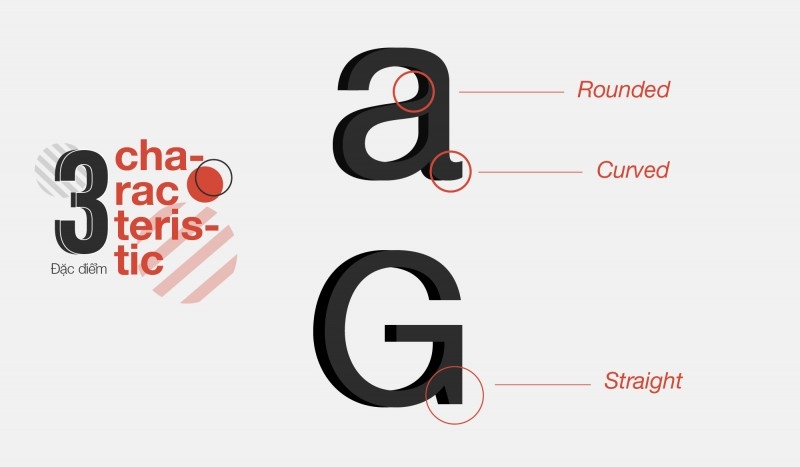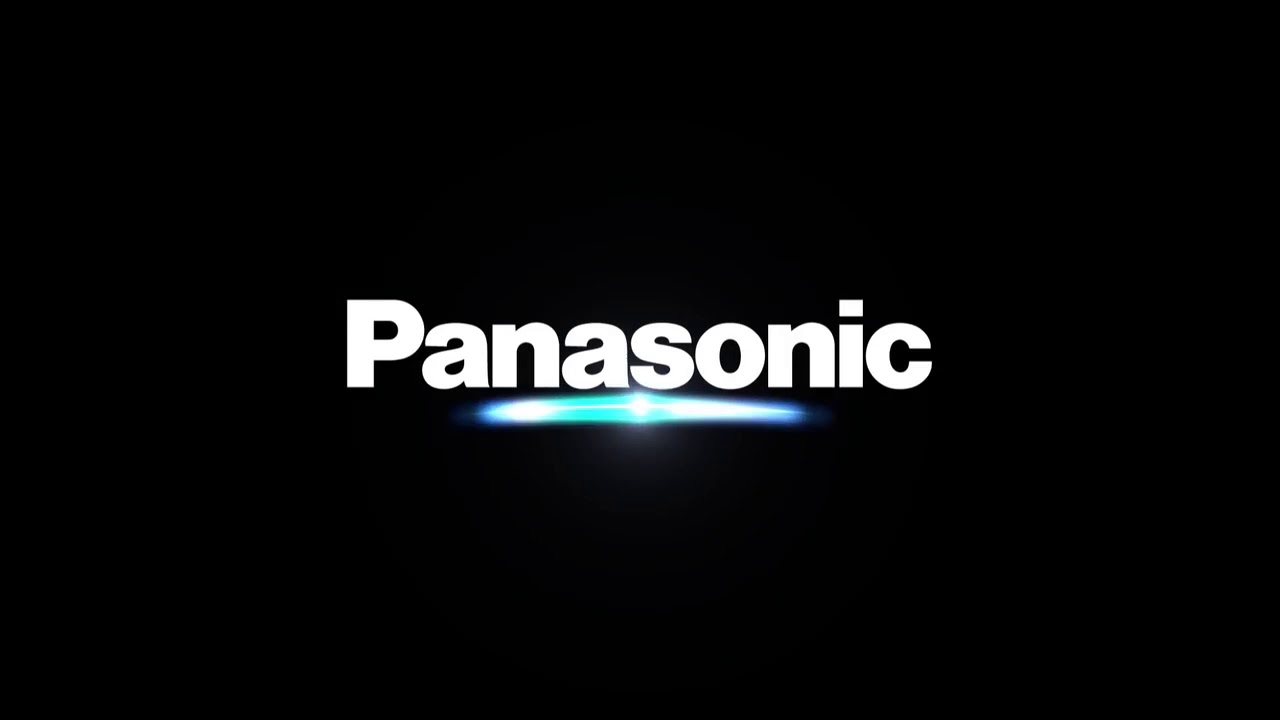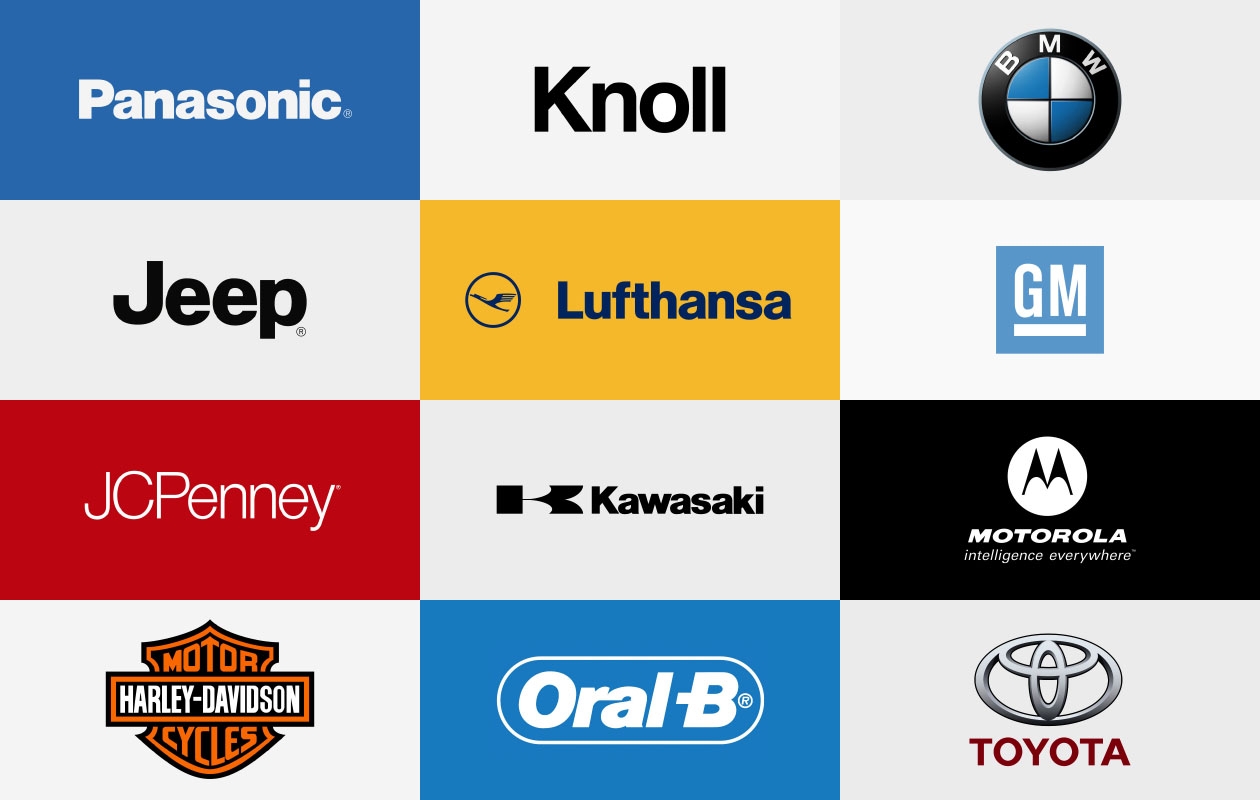
Tổng hợp 30 font Helvetica đẹp nhất hiện nay
Font Helvetica là gì?
Helvetica là một trong những font chữ sans-serif nổi tiếng và phổ biến nhất thế giới, được thiết kế vào năm 1957 bởi Max Miedinger và Eduard Hoffmann tại Thụy Sĩ. Cái tên “Helvetica” bắt nguồn từ từ Latin có nghĩa là “Thụy Sĩ”, thể hiện tinh thần hiện đại, trung lập và dễ tiếp cận – đúng như phong cách thiết kế của font này.
Với đường nét gọn gàng, cân đối và dễ đọc, Helvetica được sử dụng rộng rãi trong các lĩnh vực như thiết kế đồ họa, in ấn, nhận diện thương hiệu, biển báo công cộng và cả trong giao diện phần mềm, website.
Lợi ích khi sử dụng font Helvetica trong thiết kế
Tính thẩm mỹ cao và chuyên nghiệp: Helvetica mang lại cảm giác hiện đại, tối giản và tinh tế. Nhờ sự trung tính trong thiết kế, nó phù hợp với nhiều ngành nghề và mục đích sử dụng khác nhau.
Dễ đọc, dễ nhận diện: Các ký tự trong Helvetica được thiết kế rõ ràng, dễ nhìn ngay cả ở kích thước nhỏ. Điều này giúp người xem tiếp cận nội dung nhanh chóng và thuận tiện hơn.
Ứng dụng rộng rãi: Helvetica phù hợp với nhiều nền tảng: từ thiết kế in ấn (poster, brochure, catalogue) đến kỹ thuật số (website, app, banner…). Bạn có thể dùng Helvetica trong cả tiêu đề lẫn nội dung mà vẫn đảm bảo sự nhất quán và chuyên nghiệp.
Được sử dụng bởi nhiều thương hiệu lớn: Các thương hiệu như BMW, Panasonic, Lufthansa, American Airlines, Jeep… đều từng (hoặc đang) sử dụng Helvetica cho hệ thống nhận diện thương hiệu, chứng minh sức mạnh và độ tin cậy của font chữ này.
Một số font nổi bật trong bộ Helvetica
Helvetica Neue
Helvetica Neue (hay còn gọi là Neue Helvetica) là phiên bản cải tiến toàn diện của Helvetica gốc, được phát hành vào năm 1983 bởi hãng D. Stempel AG. Điểm nổi bật nhất của Helvetica Neue là bộ trọng số rất phong phú, bao gồm các tùy chọn như Ultra Light, Thin, Light, Regular, Medium, Bold, Black, và cả Italic cho từng mức.  Apple từng sử dụng Helvetica Neue làm font mặc định trên iOS 7 đến iOS 9, trước khi chuyển sang font San Francisco.
• Ưu điểm: Đem lại sự linh hoạt cao trong thiết kế, cho phép người dùng dễ dàng điều chỉnh độ dày mỏng của chữ theo mục đích sử dụng.
• Ứng dụng: Được dùng nhiều trong giao diện người dùng, hệ điều hành, website và ấn phẩm in ấn.
Helvetica Now
Font được ra mắt năm 2019 bởi Monotype, Helvetica Now là phiên bản tái thiết kế toàn diện dựa trên tinh thần Helvetica gốc nhưng được tinh chỉnh để phù hợp với các yêu cầu hiện đại, đặc biệt là trong môi trường số. Đặc điểm nổi bật:
• Có hơn 40 kiểu chữ khác nhau.
• Bao gồm ba bộ chính: Helvetica Now Micro (cho kích thước nhỏ), Helvetica Now Text (dành cho văn bản thông thường), và Helvetica Now Display (cho tiêu đề, kích thước lớn).
• Khoảng cách chữ, tỷ lệ và độ nét đều được tối ưu để hiển thị tốt trên mọi loại màn hình từ điện thoại đến bảng LED.
• Giải quyết triệt để những vấn đề đọc kém của Helvetica cũ khi hiển thị ở kích thước nhỏ.
Helvetica Rounded
Helvetica Rounded là phiên bản được bo tròn ở các góc chữ, tạo cảm giác mềm mại và thân thiện hơn so với phong cách góc cạnh gốc của Helvetica, đem lại sự vui vẻ, ấm áp, giúp thiết kế bớt “cứng” và dễ tiếp cận hơn.
Ứng dụng: Thường thấy trong các thiết kế dành cho trẻ em, thương hiệu mang tính gần gũi (đồ ăn, ứng dụng học tập, sản phẩm tiêu dùng…)
Helvetica Condensed / Extended
Đây là các biến thể được tinh chỉnh về chiều ngang của ký tự:
• Helvetica Condensed: Các chữ cái được nén lại hẹp hơn, giúp tiết kiệm không gian ngang – rất hữu ích trong thiết kế bố cục chật hẹp như banner, tiêu đề, cột báo…
• Helvetica Extended: Ký tự được kéo rộng ra, tạo cảm giác “thoáng”, mạnh mẽ, thường dùng cho các tiêu đề lớn, bảng hiệu hoặc áp phích quảng cáo.
• Ưu điểm: Dễ dàng cân đối thiết kế, đặc biệt khi làm việc với không gian giới hạn hoặc cần nhấn mạnh thông điệp ngắn gọn.
Helvetica luôn là lựa chọn an toàn và hiệu quả cho mọi dự án cần sự chỉn chu, hiện đại và dễ tiếp cận.